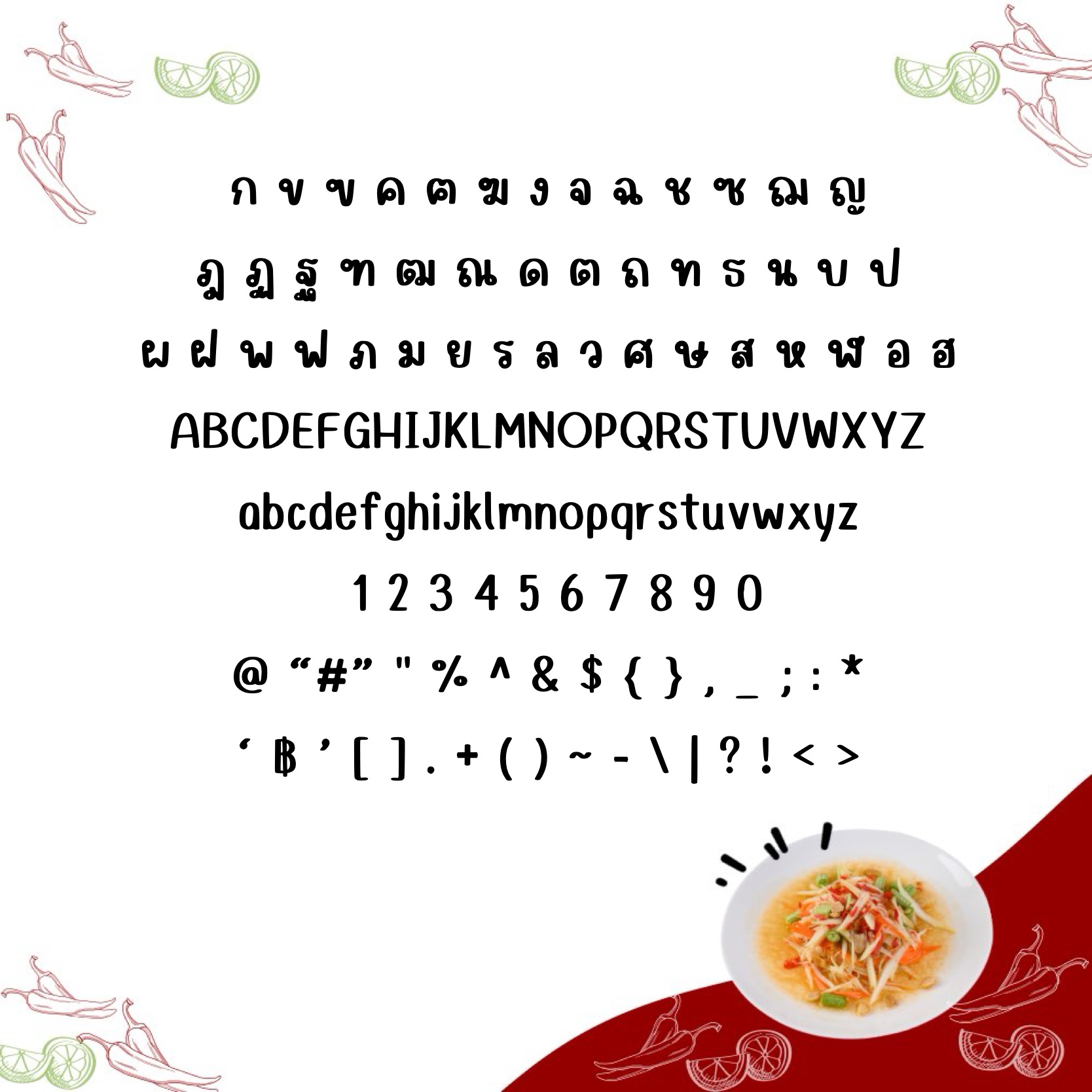
ตำไทย (Tumthai)
ฟอนต์ลายมือ ตำไทย (Tumthai)
แจกฟรี !! ฟอนต์ลายมือ ตำไทย (Tumthai) สำหรับใช้งานส่วนตัว 1 น้ำหนัก(บาง) สามารถใช้งานได้หลายรูปแบบ ไม่ว่าจะเป็นจดโน็ต สรุปงาน *สำหรับการตกแต่งป้ายสินค้า โปสเตอร์ ทำสื่อโฆษณาสินค้า จะเป็นในรูปแบบเชิงพาณิชย์ค้าบบบ